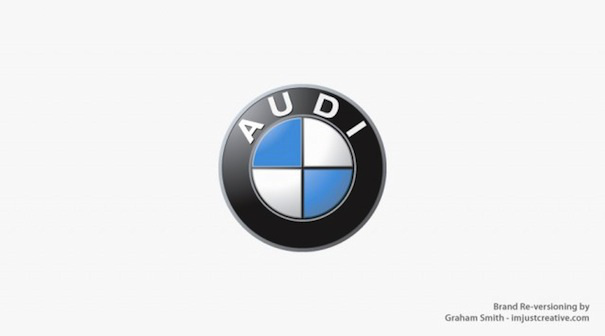
Wort oder Bildmarke im Modebereich
Ein markenstarker Auftritt hängt nicht allein vom Logo ab.
In der Tat. Nichtsdestotrotz ist die Wortmarke austausch- und verwechselbar. Was ist dein Punkt gegenüber der Aussage von Martin?
ich wüsste nicht wo sich amerian apparel (die sind übrigens pleite) und american airlines (die haben mittlerweile eine andere type) so begegnen, dass diese unternehmen miteinander verwechselbar sind. die reinen schriftzüge sind es vielleicht aber eigentlich auch nicht, denn das auge ließt ja apparel und airlines.
je nachdem wie marken um die satzschrift-wortmarke ausbaut, desto weniger kann die marke verwechselt werden, ich finde man sollte das gesamte erscheinungsbild betrachten und marken nicht nur auf ihre logo bzw. ihre satzschrift reduzieren. helvetica ist da ein schönes beispiel.
Wortmarke austausch- und verwechselbar
... austauschbar ja, verwechselbar eher nö.
… ich finde man sollte das gesamte erscheinungsbild betrachten und marken nicht nur auf ihre logo bzw. ihre satzschrift reduzieren. helvetica ist da ein schönes beispiel.
Ja, unbedingt. Aber diese Diskussion brauchen wir auch gar nicht führen. Das hat hier niemand bezweifelt.
... austauschbar ja, verwechselbar eher nö.
Doch, na klar. Ersetze mal die Helvetica durch eine Suisse, Akzidenz Grotesk, Graphik usw. Die Wenigsten werden einen Unterschied bemerken.
okay, dann haben wir aneinander vorbei geredet.
ich meinte die marken sind nicht verwechselbarer nur weil sie aus einer helvetica gesetzt ist.
du vergleichst die schriftarten an sich. aus lufthansa etc. wird also kein anderes logo wenn man es in einer suisse oder graphik setzt, dem stimme ich zu.